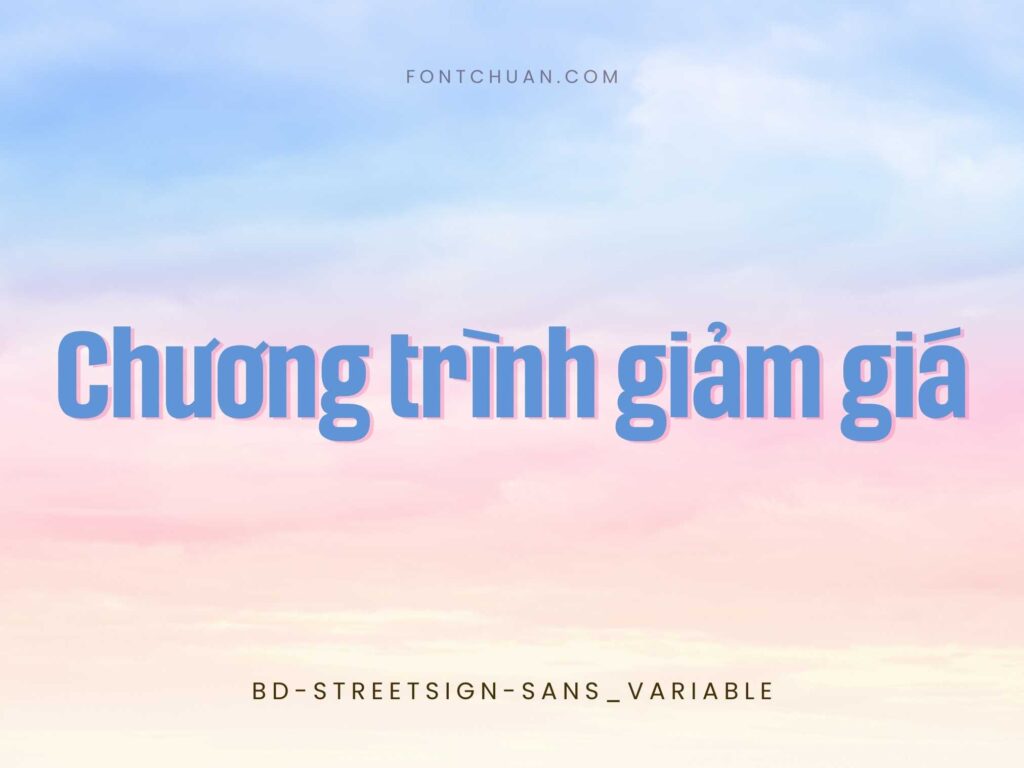
BD-StreetSign-Sans là phiên bản Việt hóa của phông chữ StreetSign Sans, được thiết kế bởi Harry Dinh. Đây là một phông chữ sans serif hiện đại, lấy cảm hứng từ các biển hiệu vẽ tay tại Việt Nam trong thập niên 80-90. Phông chữ này mang đậm nét văn hóa đường phố Việt Nam, kết hợp giữa sự hoài cổ và hiện đại. Phiên bản BD-StreetSign-Sans v2.0 được phát hành vào năm 2024, bao gồm 16 biến thể và hỗ trợ đầy đủ tiếng Việt, giúp người dùng dễ dàng áp dụng trong các dự án thiết kế đa dạng. Ngoài tiếng Việt, phông chữ còn hỗ trợ nhiều ngôn ngữ khác, bao gồm tiếng Anh, Pháp, Tây Ban Nha, Đức và Ý. Phông chữ này được thành viên Font Chuẩn sưu tầm và đăng tải nhằm phục vụ nhu cầu sáng tạo phong phú.
Với thiết kế đậm nét và hình học, BD-StreetSign-Sans phù hợp cho các ứng dụng như thiết kế biển hiệu, poster, logo và các ấn phẩm cần sự nổi bật và cá tính. Các ký tự có tỷ lệ độc đáo và nhiều hình dạng khác nhau, tạo cảm giác ngẫu hứng nhưng vẫn đồng nhất. Trong lĩnh vực sự kiện, phông chữ này có thể được sử dụng trong các dịp như lễ hội, thiệp cưới và sinh nhật. Ngoài ra, BD-StreetSign-Sans cũng thích hợp cho các ngành nghề như quảng cáo, giáo dục và công nghệ.